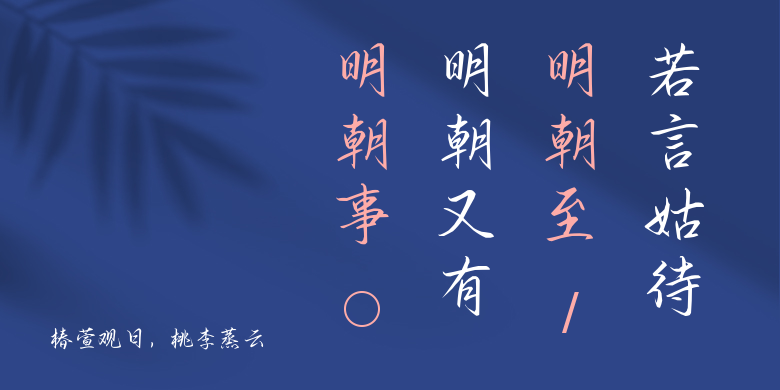
椿萱观日,桃李蒸云
椿萱观日,桃李蒸云,这款字体结构工整、笔画清晰,兼顾美观与易读性,适用于标题、正文、海报、包装、LOGO 等多种场景。字形优雅稳定,风格百搭耐看,适配日常排版与创意设计,让文字呈现更舒适、更具质感。椿萱观日,桃李蒸云一笔一画,皆是细节,以均衡的比例、流畅的线条打造舒适视觉体验,字形端正大气,风格简约现代。无论是商业设计、品牌宣传还是日常排版,都能轻松驾驭,让文字更有格调与力量。椿萱观日,桃李蒸云字体下载。